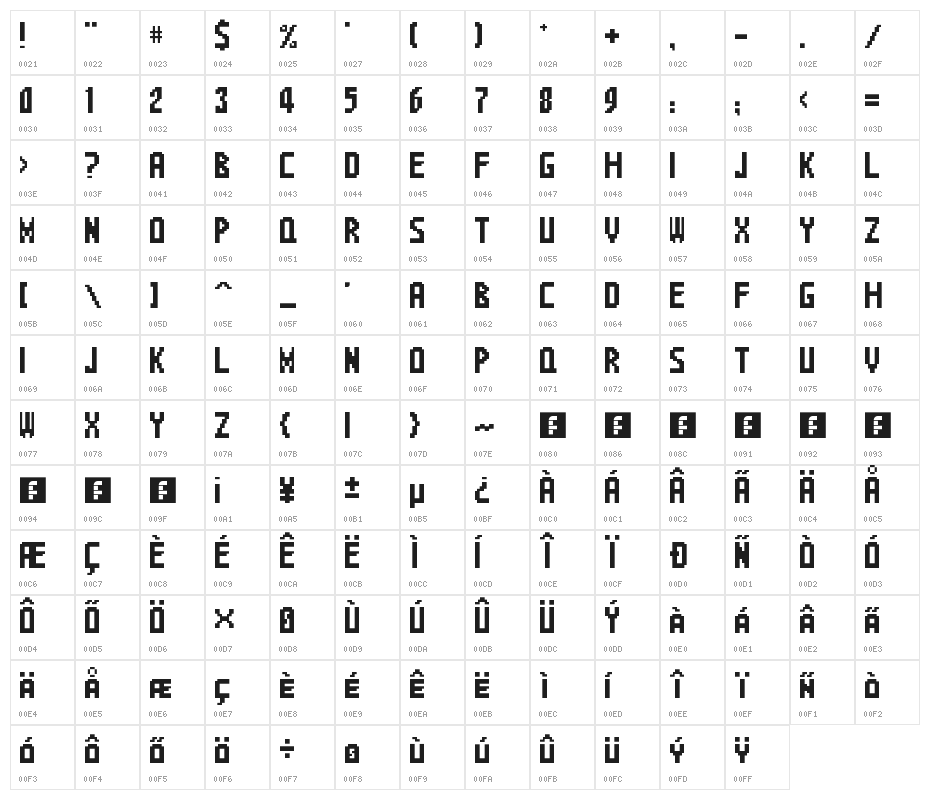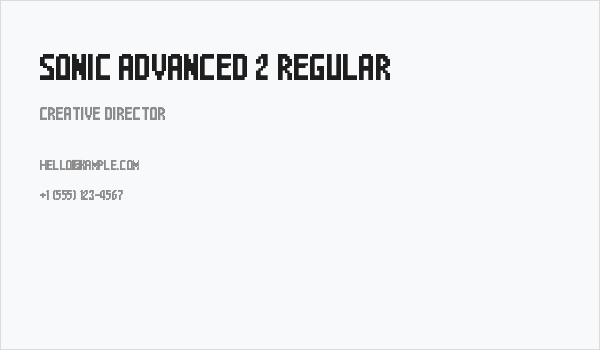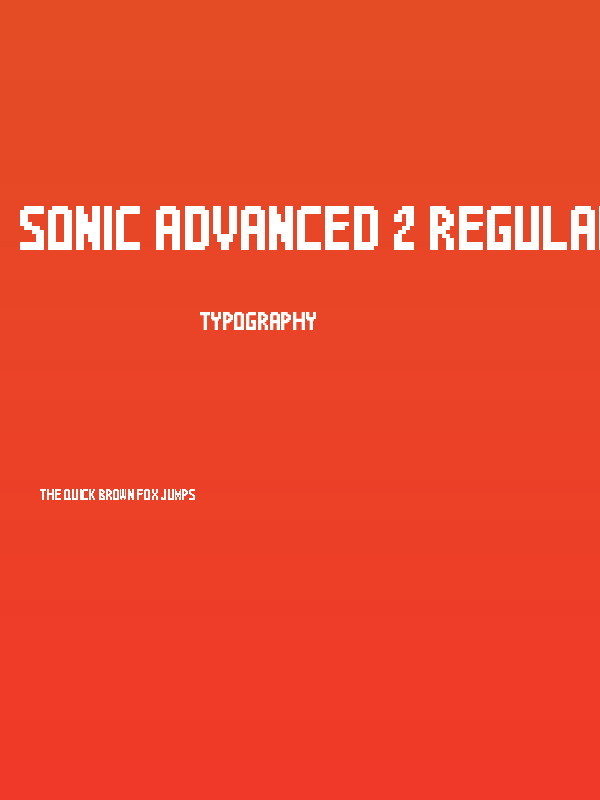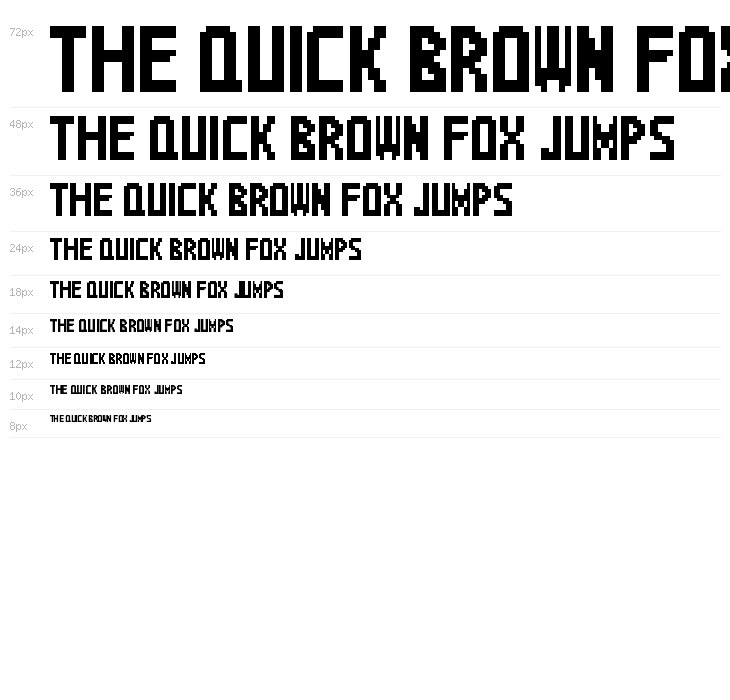
Sonic Advanced 2 Regular Font
| Kategorien | Pixel |
| Gesamtstil | Retro, Digital |
| Vorgeschlagene Projekte | Ideal for video game design, retro-themed posters, digital art, and tech-related branding. |